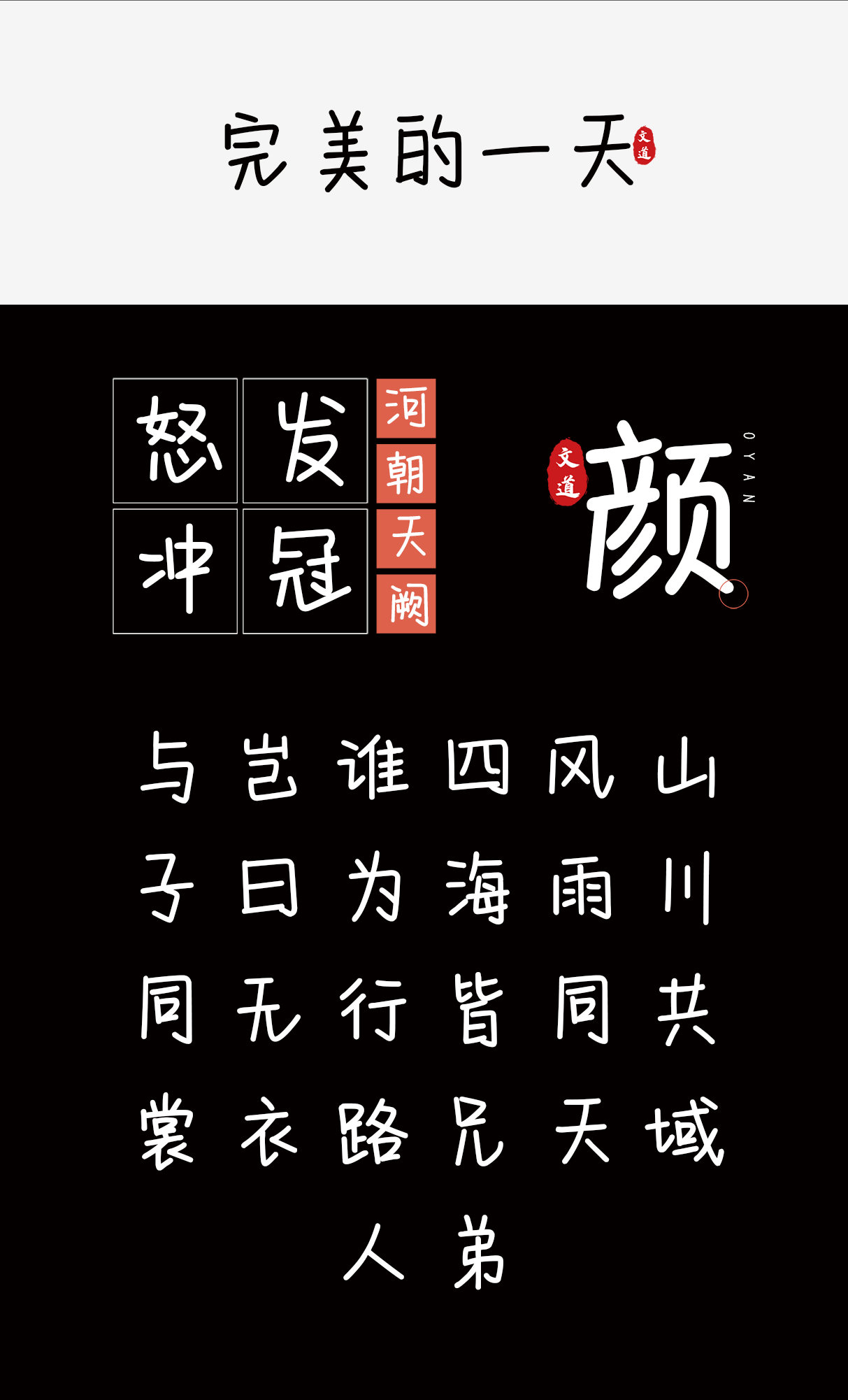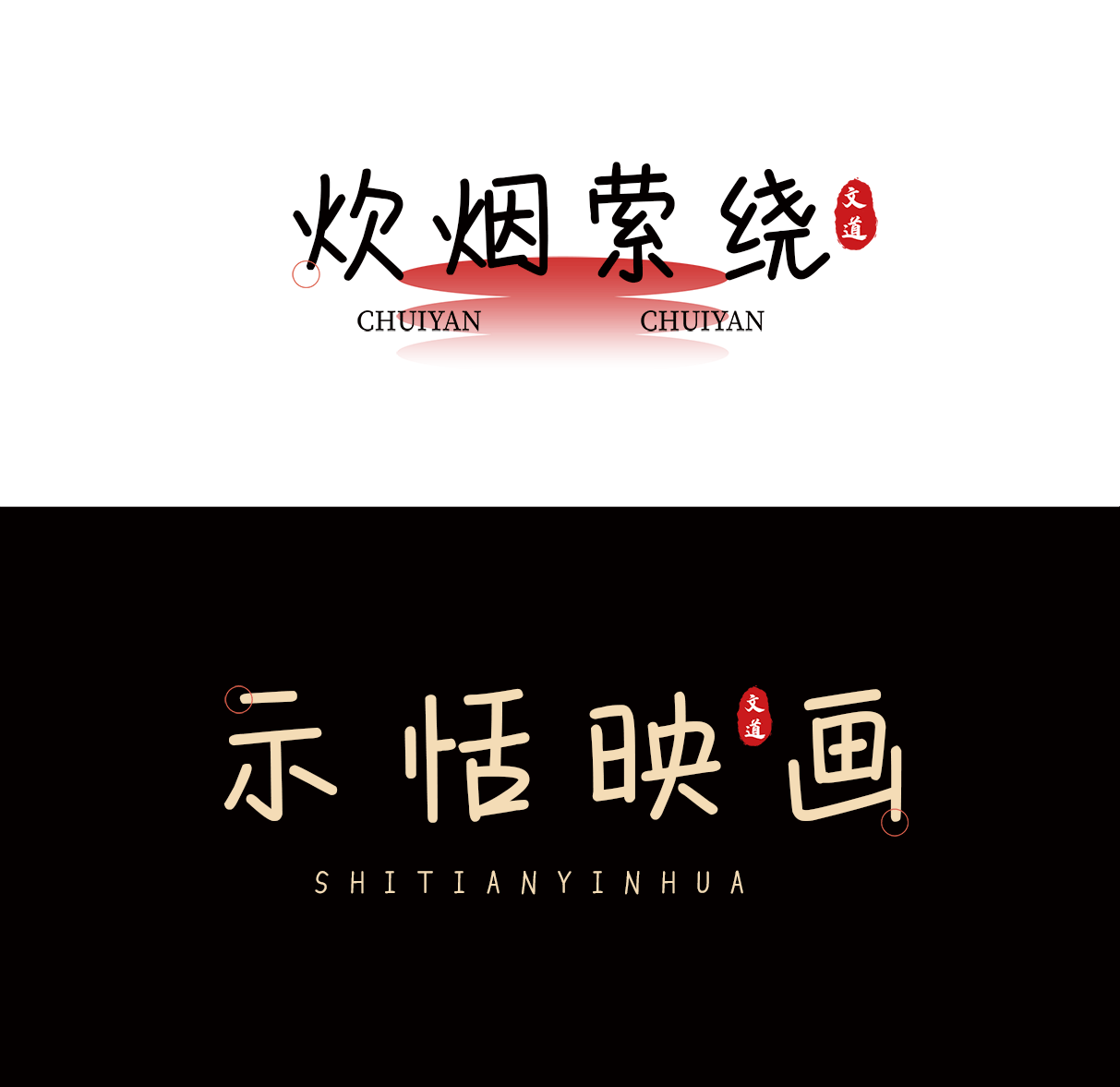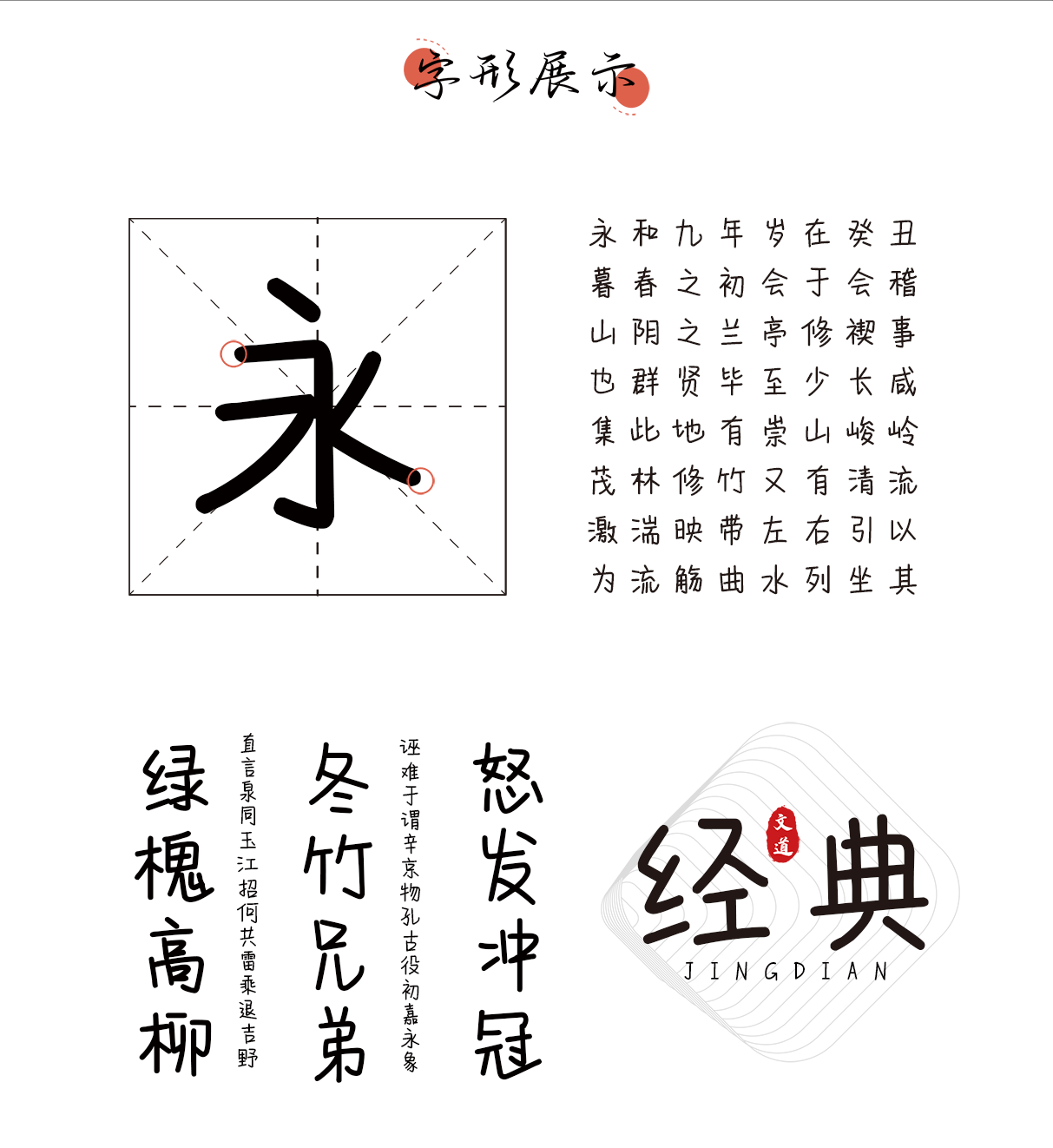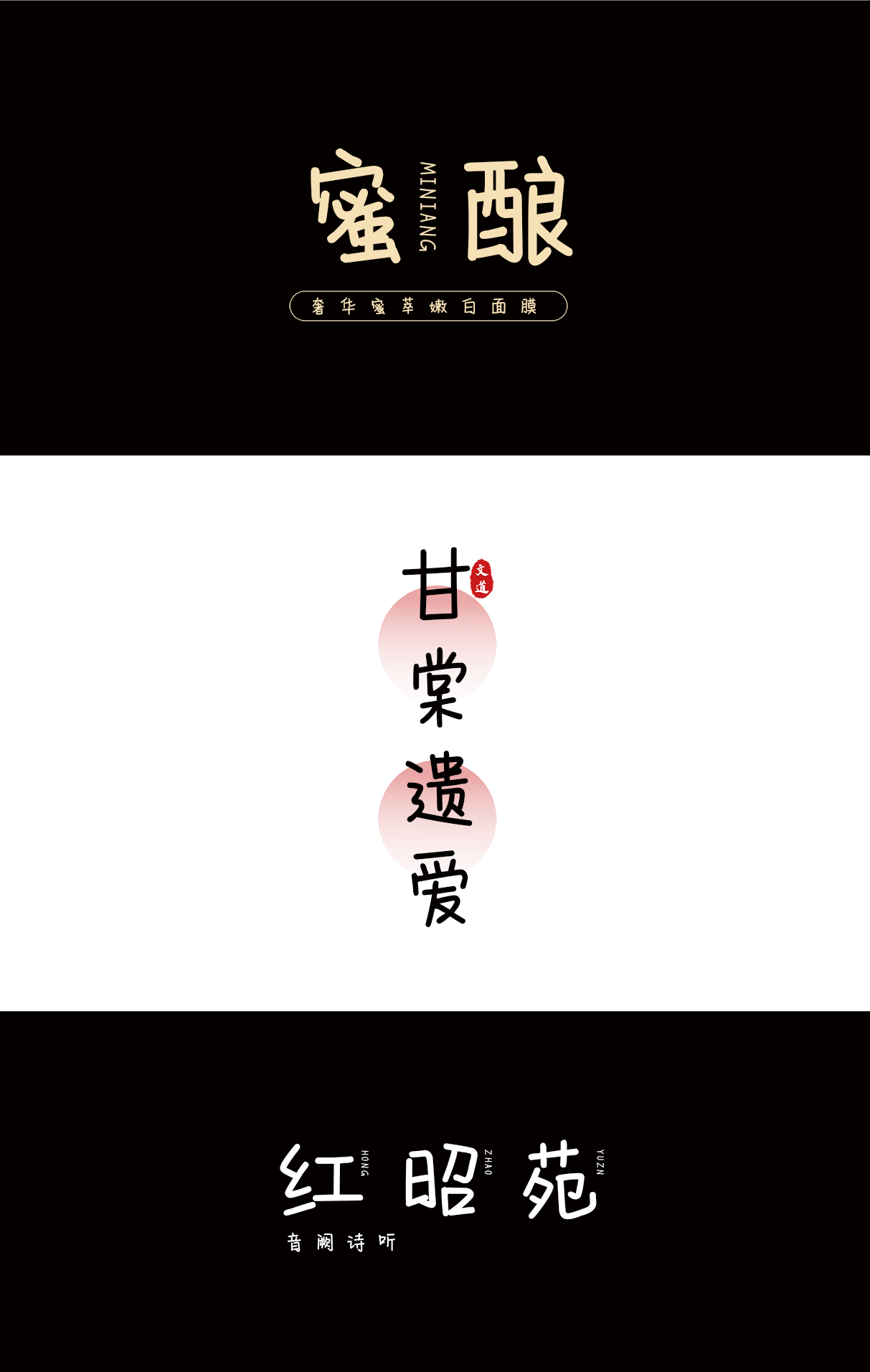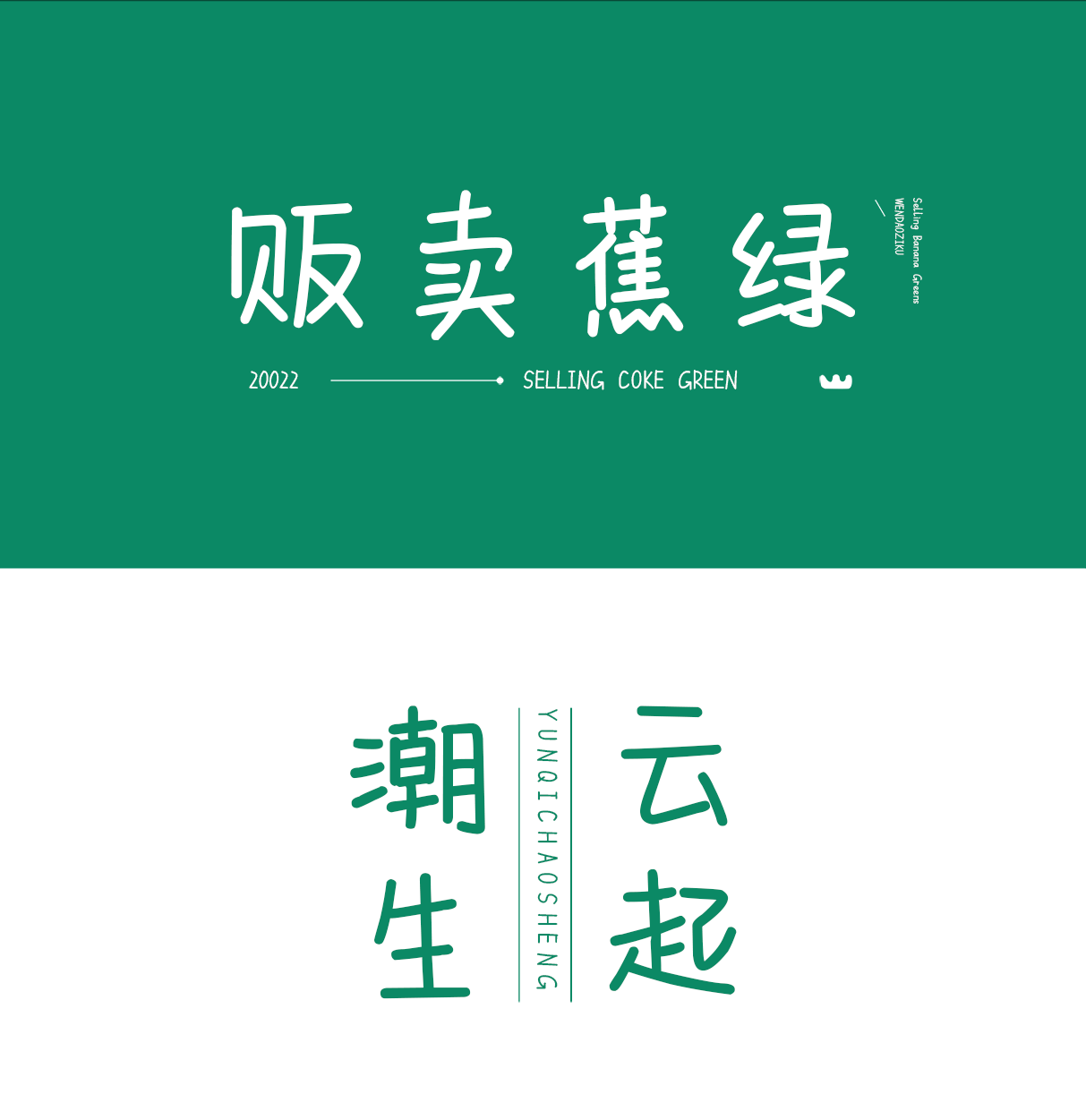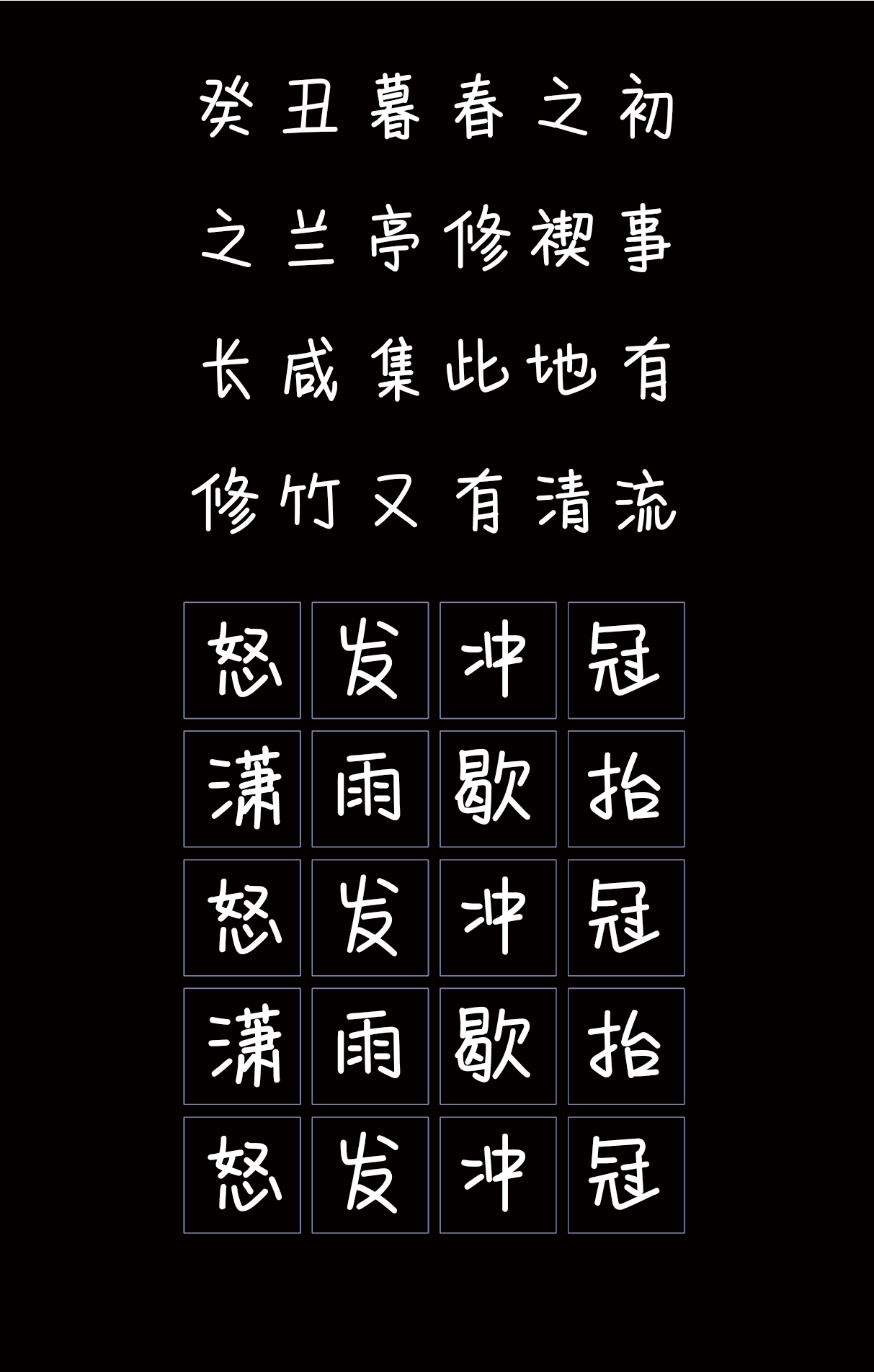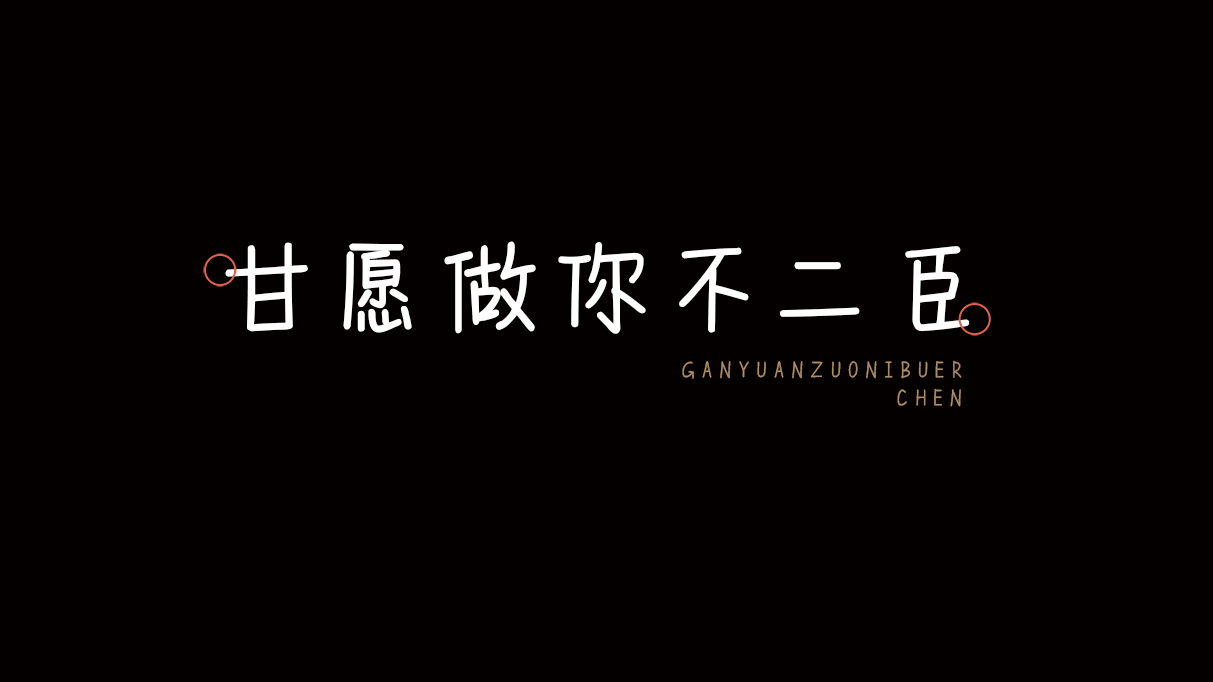
甘愿做你不二臣
文亦有道,笔墨添香;墨韵飞扬,意蕴绵长。
字体名称: 甘愿做你不二臣
简介: 【甘愿做你不二臣】这是一款可商用创意体,整齐划一的笔画衬托出极具简约的风格,该字包含6763个中文、字母、符号和数字,可用于印刷媒介的各类标题,还适用于屏幕显示、广告标语和环保性能产品、小清新产品类包装设计